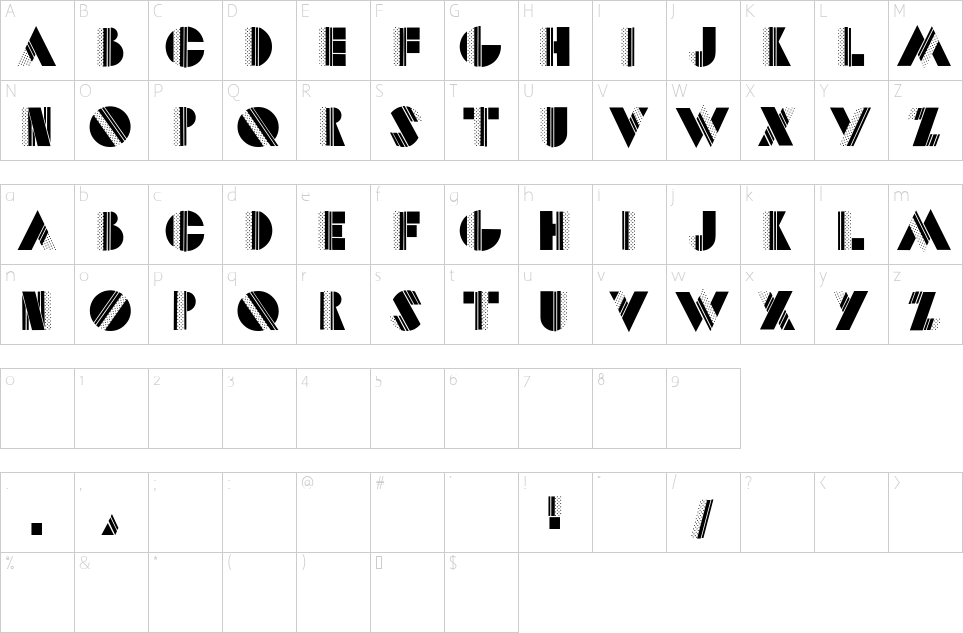
Descubra a Dots Caps Two font, uma elegante opção para seu próximo projeto de design. Esta fonte foi criada pelo designer Manfred Klein e já recebeu downloads de mais de 6.640 pessoas que valorizam sua capacidade única de destaque os títulos em ambientes digitais. Com um ar sofisticado, a Dots Caps Two oferece um estilo inovador com seu design capcioso e icônico. Suas letras fortes são perfeitas para destacar o texto importante na sua página ou documento. Seja você designer gráfico, blogueiro ou até mesmo webmaster, essa fonte será uma ótima escolha. Descubra agora a Dots Caps Two e deixe seu design se destacar ainda mais com esta fantástica opção de fontes grátis para Windows e Mac.